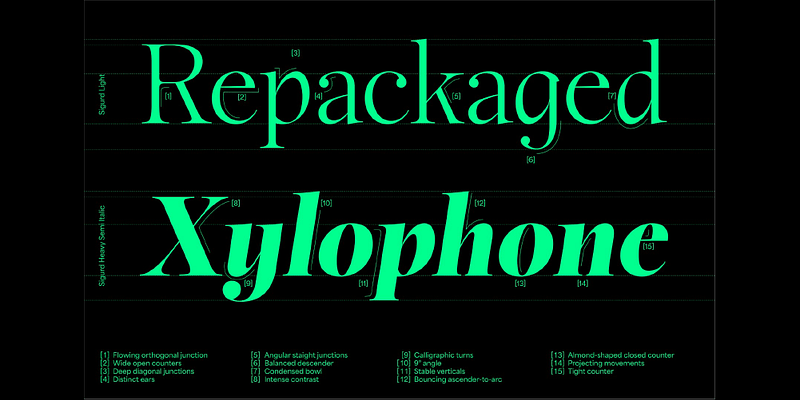
Sigurd는 Nibelungen Saga의 영웅 Siegfried에게서 영감을 받았습니다. Sigurd는 칼 모양, 봉건 갑옷, 중세 문자 작업에서 영감을 얻습니다. 강력한 디자인 구성과 수많은 대체 문자 및 다양한 스와시가 포함된 우아한 글꼴 패밀리로, 다양한 텍스트 레이아웃 용도 및 디스플레이 용도에 적합합니다.